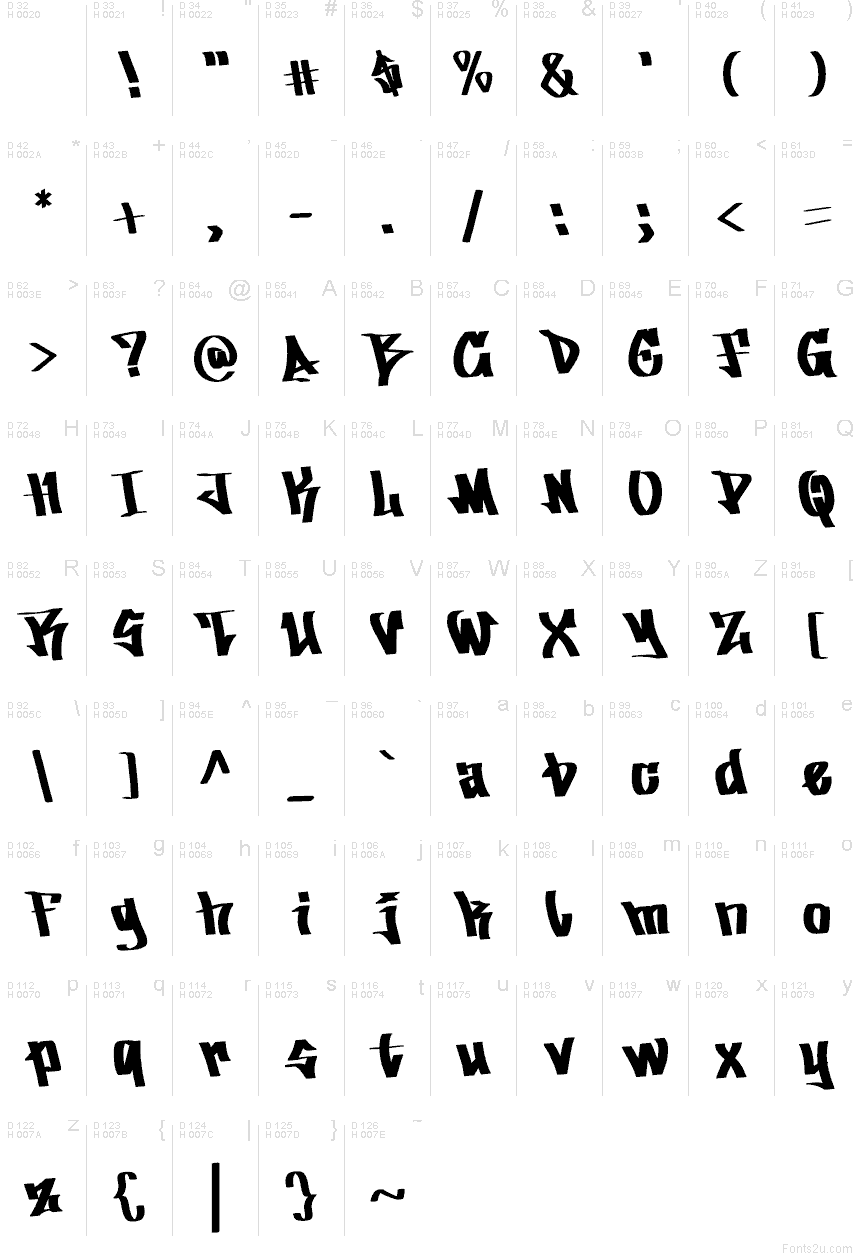
Blastoria هو خط جرافيتي مجاني يتميز بضربات حادة وزوايا قاطعة وتكوينات خشنة تبدو وكأنها رُسمت بسرعة باستخدام قلم تحديد أو بخاخ طلاء. تستخدم الحروف زوايا مائلة وحوافاً مدببة وإيقاعاً متحرراً، مما يمنح التصميم مظهراً حضرياً وعفوياً دون أن يفقد قوته البصرية.
يعد خط Blastoria مثالياً لعناوين الملصقات، وتصاميم أزياء الشارع، وأغلفة الألبومات الموسيقية، ومنشورات الفعاليات، والشعارات، واللافتات الجدارية، حيث تحتفظ أشكاله المكسورة بطاقتها حتى في الأحجام الكبيرة. هذا الخط المجاني مناسب أيضاً لتصاميم الملصقات، وجرافيك وسائل التواصل الاجتماعي، واللمسات التحريرية الجريئة عندما تبحث عن حروف تبدو خاماً ومباشرة ومتجذرة في ثقافة الشارع.